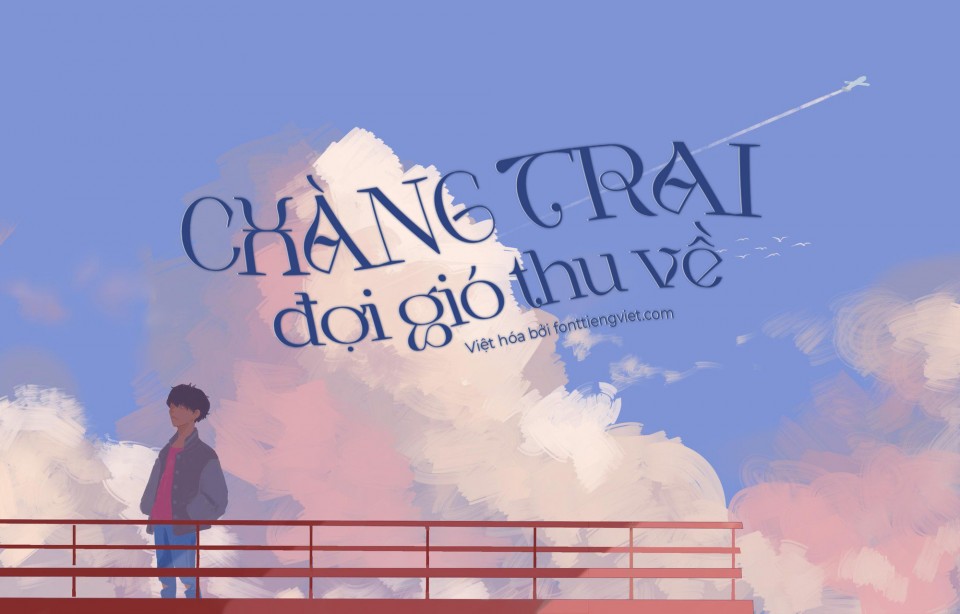
Font việt hóa 1FTV Vako Mave
Trong thế giới đồ họa hiện đại, việc tìm kiếm một bộ Font Miễn Phí chất lượng luôn là ưu tiên hàng đầu của các nhà thiết kế. Font việt hóa 1FTV Vako Mave nổi lên như một lựa chọn hoàn hảo nhờ sự kết hợp giữa nét cổ điển và tinh thần đương đại. Bộ font này không chỉ mang lại vẻ đẹp thẩm mỹ cao mà còn đảm bảo tính ứng dụng linh hoạt trên nhiều nền tảng khác nhau từ in ấn đến hiển thị kỹ thuật số.
Đặc điểm nổi bật của Font việt hóa 1FTV Vako Mave
Phong cách thiết kế độc đáo
Bộ font này sở hữu những đường nét mạnh mẽ nhưng không kém phần uyển chuyển, giúp các biểu ngữ hay tiêu đề trở nên nổi bật hơn. 1FTV Vako Mave được tinh chỉnh kỹ lưỡng về khoảng cách và chân chữ, tạo cảm giác chuyên nghiệp và dễ đọc cho người xem. Đây là công cụ đắc lực để truyền tải thông điệp một cách ấn tượng nhất trong các dự án sáng tạo.
Khả năng tương thích và Việt hóa hoàn chỉnh
Điểm cộng lớn nhất chính là khả năng hỗ trợ đầy đủ các dấu tiếng Việt, giúp người dùng không còn lo lắng về lỗi hiển thị hay mất ký tự khi soạn thảo. Font đã được tối ưu hóa để tương thích tốt với các phần mềm thiết kế phổ biến như Adobe Photoshop, Illustrator hay Canva, giúp quy trình làm việc trở nên mượt mà và hiệu quả hơn rất nhiều.
Ứng dụng thực tế của font chữ trong giáo dục và đời sống
Với phong cách thanh lịch, bộ font này rất phù hợp cho các bài thuyết trình, thiết kế tài liệu học tập hoặc làm thiệp mời tại nhà trường. Sự rõ ràng của các ký tự giúp học sinh dễ dàng tiếp nhận thông tin, đồng thời kích thích sự sáng tạo trong quá trình thực hiện các dự án nhóm. Bên cạnh đó, các bạn cũng có thể sử dụng font để làm bìa sách hoặc trang trí blog cá nhân thêm phần sinh động.